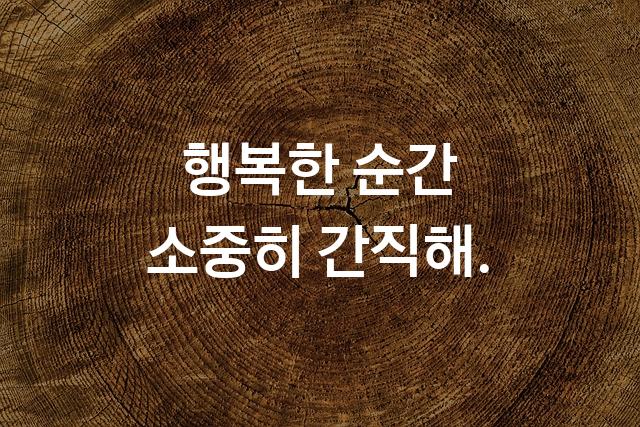
카카오 작은글씨는 카카오에서 제작한 기본 고딕 폰트로, 작은 글씨에도 뛰어난 가독성을 제공합니다. 세련되고 깔끔한 디자인이 특징입니다.
카카오 작은글씨은(는)
기본 고딕, 감성적인, 부드러움 계열의 생김새를 가지고 있으며
프레젠테이션, 보고서/문서, 일기/편지 등에서 자주 활용되며, 효과적인 메시지 전달에 적합합니다.
이 폰트는 교육, 출판/미디어, 금융/비즈니스 분야에 잘 어울리며,
명확한, 편안한, 단순한 느낌을 담고 있는 것이 특징입니다.